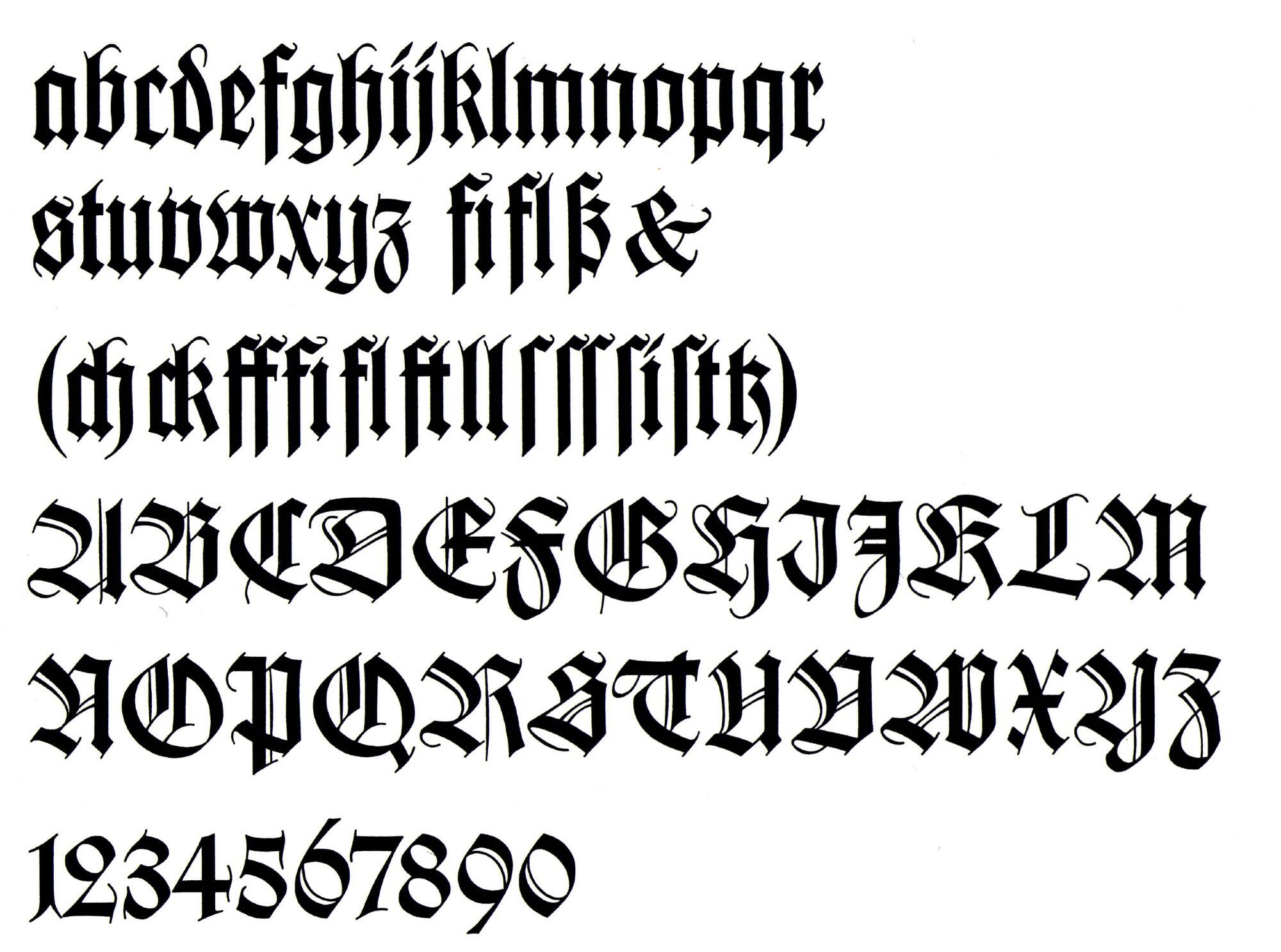
- circa 1925
- Gebrochene Schrift
Die Wilhelm Klingspor Gotisch von Rudolf Koch erschien 1925 bei den Gebrüdern Klingspor in Offenbach. Sie ist nach der kräftigen Maximilian (Entwurf 1913–14) Kochs zweite gotische Schrift, die nun deutlich edler und schlanker erscheint.
Die Klingspor Gotisch geht auf einen 1918 von Koch geschriebenen Text zurück (siehe Abbildung). Karl Klingspor regte an, daraus eine Satzschrift zu entwickeln. Von 1920 bis 1926 wurde daran gearbeitet – ein vergleichsweise langer Zeitraum für einen einzelnen Fettegrad. In der damaligen Schriftprobe heißt es dazu sinngemäß »obwohl unsere Zeit nicht die Unternehmung von so anspruchsvollen Druckwerken erlaubt wie die Zeit Gutenbergs, wir doch das Verlangen haben, in der Güte und Schönheit unserer Arbeit nicht hinter den Alten zurückzustehen; so sei diese Schrift für Aufgaben gedacht, für die unsere glatten Gebrauchsschriften nicht ausreichen und die, aus den Bedürfnissen unserer Zeit geboren, erhöhten Anspruch auf Schrift und Satzwirkung erheben.«
Die folgende Darstellung zeigt die ersten Probeschnitte:
Jedoch kam man zur Überzeugung, dass die Schrift noch zu kräftig war, und schnitt alle Grade noch einmal neu:
Eine Besonderheit der Schrift sind die Varianten. Im Geiste Gutenbergs wurden für viele Buchstaben verschiedene Breiten entworfen, sodass man im Satzbild die jeweils passenden wählen konnte.
Im Gedenken an den 1925 verstorbenen Bruder Karl Klingspors wurde die Schrift als Wilhelm Klingspor Gotisch herausgebracht.
Die Linotype-Digitalisierung benutzt einige Antiqua-artige Buchstabenformen, die den heutigen Lesegewohnheiten angepasst sind, jedoch nicht den Originalentwürfen Kochs entsprechen.
Die Digitalisierung von José Alberto Mauricio aus dem Jahr 2013 enthält jedoch die ursprünglichen Zeichenvorrat inklusive aller Varianten und einiger passender Zierstücke.